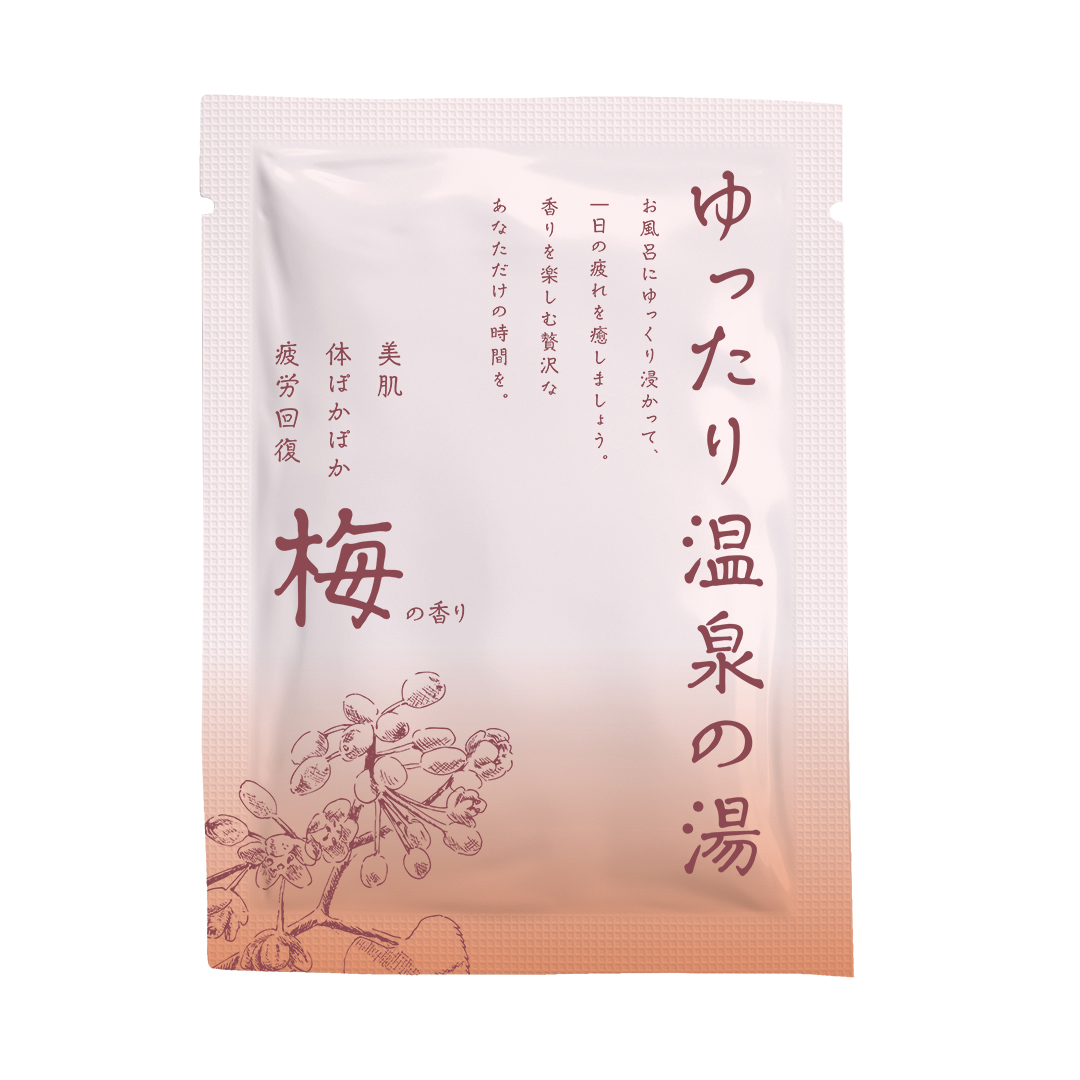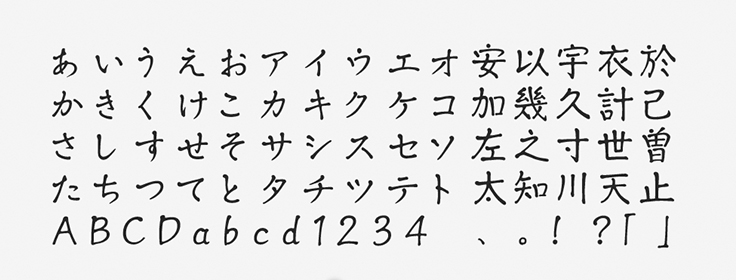
「小琴 京かな」について
小琴 京かなは優しい印象を与える手書き系のデザインフォントで、2019年秋に提供が開始されました。同時リリースされた小琴 遊かなと共通する漢字で構成されています。小琴 遊かなが楽しい雰囲気のかな文字である一方、小琴 京かなにはレトロで素朴な印象のかな文字が採用されています。
「小琴 京かな」の特徴
力の抜けた優しい風合いが大きな魅力です。手書きの雰囲気をたっぷりと残しつつ、部分的に点のエレメントが丸の形で表現されているなど、楽しいアクセントも加えられた独特なデザインに仕上げられています。
かな文字はゆったりとした運筆で丁寧に書かれた印象です。漢字は始筆や収筆の部分にもやや丸みが持たせてあり、柔らかなイメージが強調されています。アンバランスな骨格であることも含めて、とても可愛らしい雰囲気を内包したフォントです。
ほど良い肉付きで柔らかい印象のフォントです。本文組みにも十分耐えうる設計だと思いますので、詩集や短歌集などにもバッチリはまりそうですね。ひらがなのデザインも素晴らしい。これまでありそうでなかったフォントだと感じますし、今後さらに人気が出そうです。